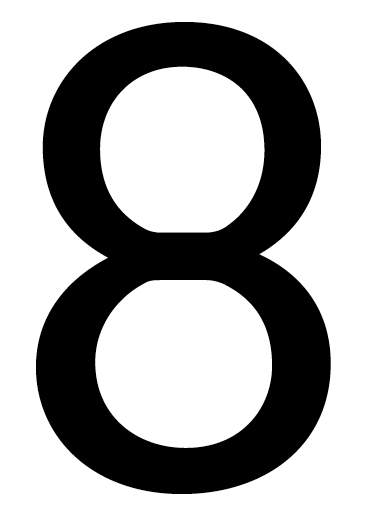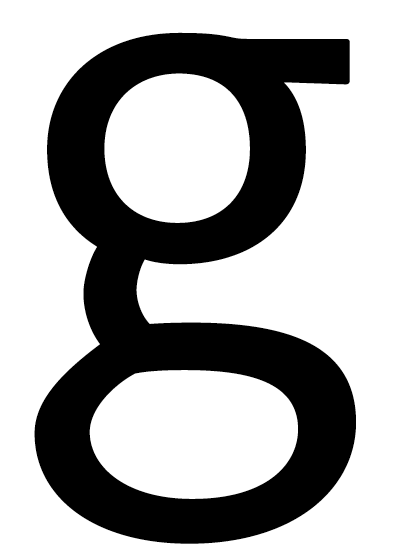
Neu: Adobe Clean
sorry guys, ok- it's a nice mix between gil and dax (not really good: small g and small k) but who needs another look-a-like font, certainly not a company like adobe! this is a heavy, extended disappointment.
Seh ich auch so. Ist eigentlich die typische Hausschriften-Masche: Wir wollen einen Font wie »FontXY«, aber da den ja jeder hat, ein etwas umgemodelt und eigen. Das Ergebnis ist dann immer entsprechend.
Aber das sowas (siehe unten) auch von Slimbach/Adobe kommt, wundert mich sehr.